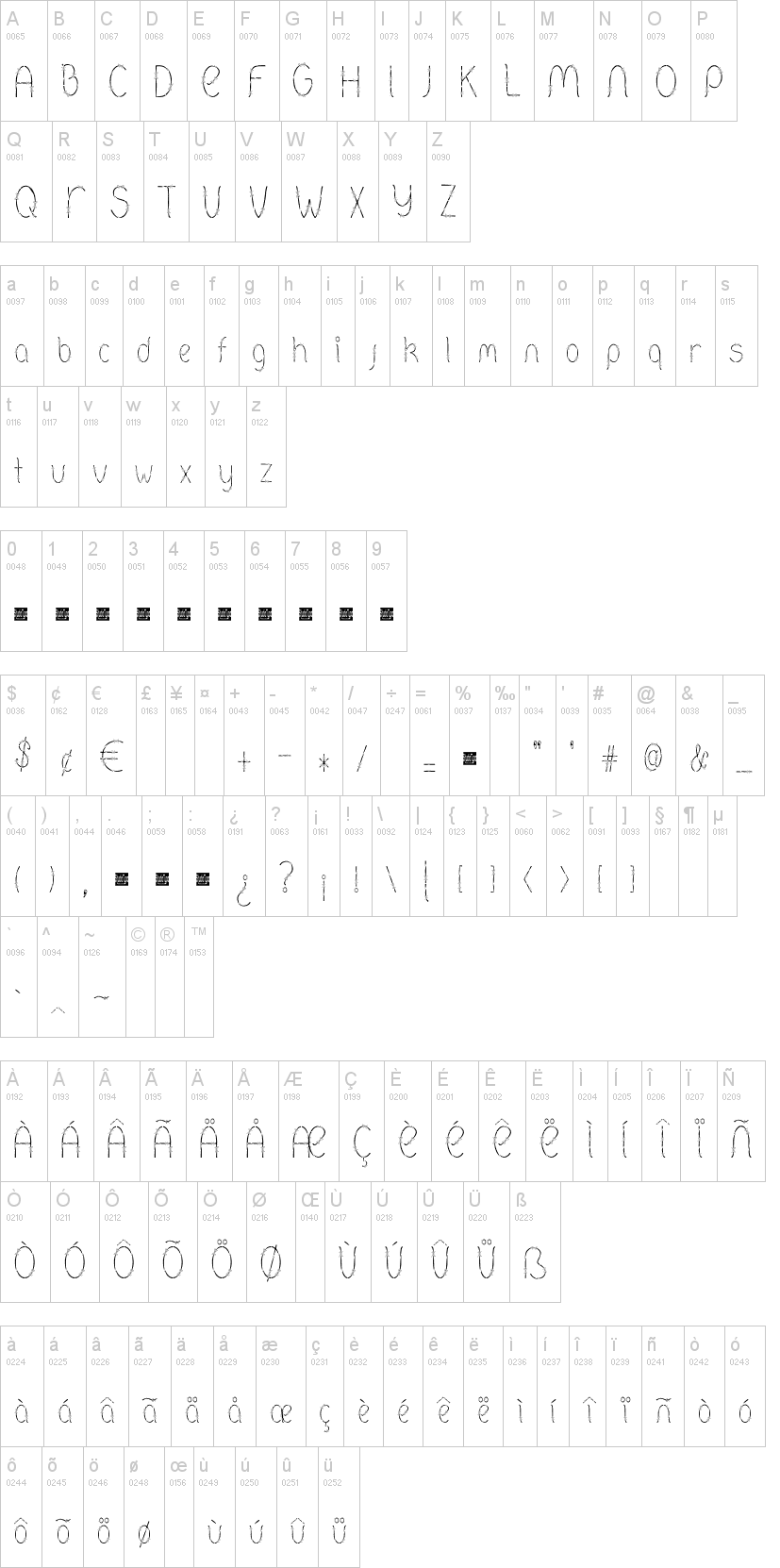
Barbed
Barbed 字体是一款由英国设计师Neil Summerour创作的一款草书字体。它具有细腻的笔画,温柔的节奏,极具艺术感的设计特点。Barbed字体的笔画和线条组合极具个性,它可以带给你极具活力的感觉,让你的文字更加生动有趣。
Barbed是一款非常不错的手写艺术字体,具有很好的视觉感,适合于文化类的宣传设计、商业类品牌的广告和产品包装设计以及个性化文字排版等较多场景。